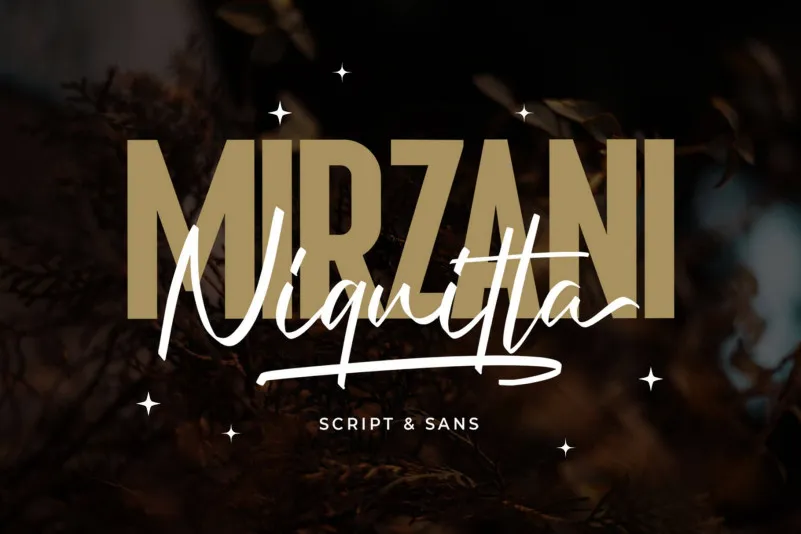
Niquitta Mirzani Font – Fonte Grátis
Niquitta Mirzani Font
A Niquitta Mirzani Font é uma fonte script que traz a essência do estilo casual e curvilíneo, com traços que lembram o uso de canetas de feltro e traços desviados para um toque divertido e único. Esta fonte foi criada pela Arterfak Project em 99designs, uma plataforma popular de criação de recursos digitais. Com seus traços suaves e suas formas estreitas, essa fonte sem serif é perfeitamente adequada para uso conjunto com outras fontes script. Ela foi projetada para dar espaços amplos e uma aparência de assinatura, pois cada letraforma foi criado através de escrever rapidamente a mão, resultando em um formato mais largo que se assemelha a uma assinatura. O resultado é uma combinação única de estilo casual e elegante. Esta fonte seria perfeita para gráficos digitais, como design de logotipos, banners online ou qualquer outro projeto onde você precisa de um charme autêntico que mantenha os olhos interessados. Com seu traço único e alegre, Niquitta Mirzani Font é uma excelente escolha para tornar seus projetos mais únicos e memoráveis.